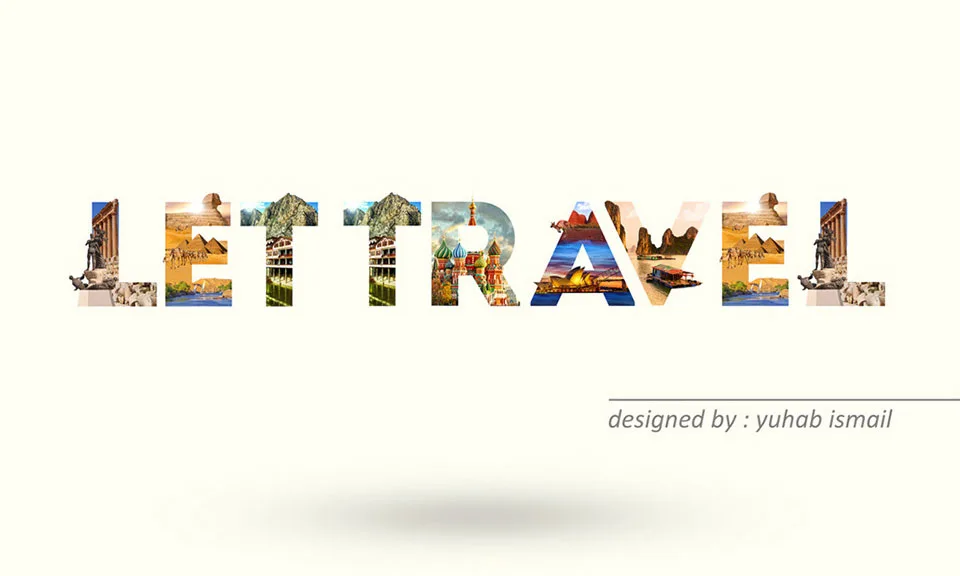
Designer une letras do alfabeto e pontos turísticos para dar referência a cada país
O designer gráfico Yuhab Ismail combinou tipografia e fotografia e criou um projeto criativo com as letras do alfabeto intitulado: “LETTRAVEL”, para representar alguns países.
Ele incluiu alguns pontos turísticos marcantes dos países mais bonitos do mundo, além de colocar elementos específicos dos países como a Alemanha, Rússia, Austrália, entre outros, dentro de uma só letra.